Fleisch
»Fleisch« ist ein typografischer Fachausdruck aus dem gewerbespezifischen Sprachschatz dspr. Schriftsetzer, Schriftgießer und Drucker aus der Periode des materiellen Schriftsatzes mit physischen Drucktypen aus Metall (z.B. aus einer Blei-Zinn-Antimon-Kupfer-Legierung), Holz (z.B. aus Birnenholz) oder Kunststoff (z.B. aus Kunstharz) für den nichtdruckenden Außenraum eines Schriftzeichens, beispielsweise eines Buchstabens, einer Arabischen Ziffer oder eines Sonderzeichens, inklusive seiner Formmerkmale, z.B. Striche, Bögen, Tropfen oder Serifen; Buchstabenaußenraum.
Der Terminus wird auch heute noch in der digitalen Typografie bzw. Schriftgestaltung bei digitalen Fonts verwendet, allerdings in seiner Beschreibung etwas leicht verändert. Das Pendant zum Fleisch eines Schriftbildes ist die Punze, der Binnenraum eines Schriftzeichens.
Die Bezugspunkte – also welcher nichtdruckender Außenraum zum Fleisch zählt – sind abhängig vom Satzverfahren. Bei physischen Drucktypen aus Metall (z.B. aus einer Blei-Zinn-Antimon-Kupfer-Legierung), Holz (z.B. aus Birnenholz) oder Kunststoff (z.B. aus Kunstharz) weicht die Bemaßung produktionsbedingt von optisch erzeugten Schriftzeichen (Fotosatz) und digitalen Fonts ab. Die Gesamtfläche des Fleisches bei optisch erzeugten Schriften und Fonts ist per Definition geringer als bei physischen Drucktypen.
Das Fleisch bei pysischen Drucktypen
Im materiellen Schriftsatz wird der gesamte nichterhabene Außenraum des Kopfes eines Schriftkegels als Fleisch bezeichnet, also alle nichterhabenen Flächen seitlich, ober- und unterhalb des erhabenen Schriftbildes eines Schriftkegels, unabhängig von Schulterhöhe, Konus, Vor- und Nachbreite. Bezugspunkte sind die äußersten Ränder des Schriftbildes und die beiden Seitenflächen, die Stirnseite und der Rücken des Kegelkopfes.
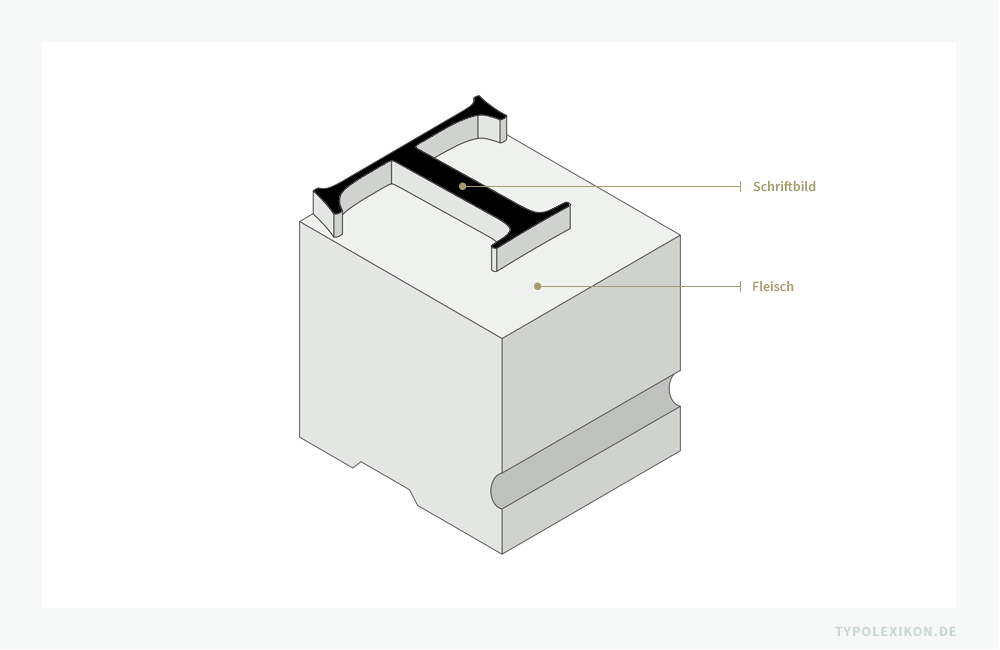
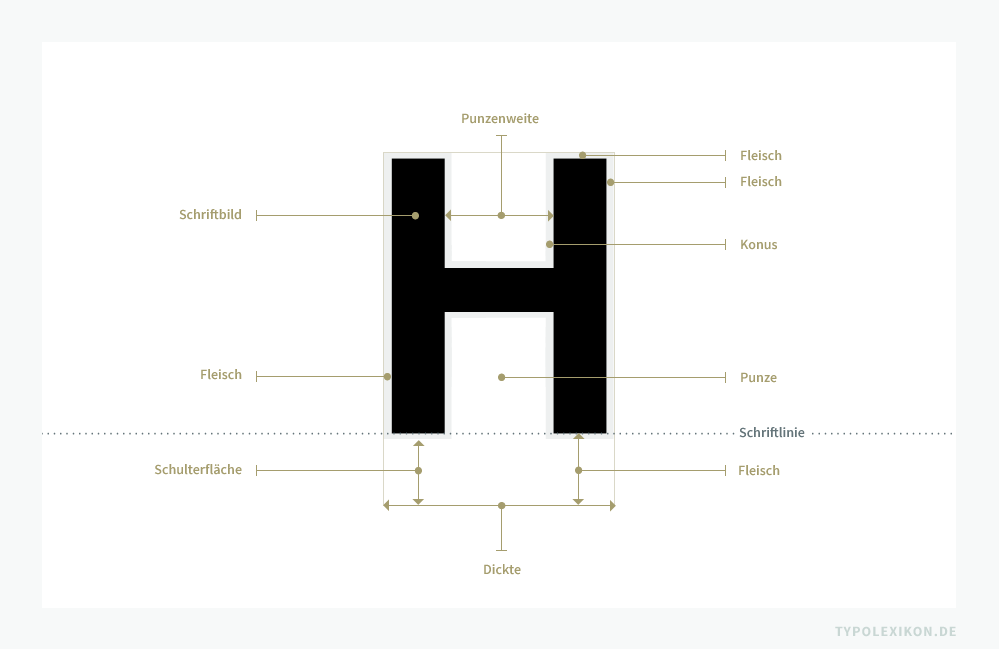Schema eines physischen Schriftkegels aus einer Blei-Zinn-Antimon-Kupfer-Legierung im normalen Breitenlauf.
Am Kopf eines Schriftkegels befindet sich das spiegelverkehrt erhabene (druckende) »Schriftbild« sowie das nicht erhabene (nichtdruckende) Fleisch inklusive Konus, Schulterfläche, Vor- und Nachbreite.
Bei physischen Drucktypen wird der gesamte nichterhabene Außenraum des Kopfes eines Schriftkegels als Fleisch bezeichnet, also alle nichterhabenen Flächen seitlich, ober- und unterhalb des erhabenen Schriftbildes eines Schriftkegels, unabhängig von Schulterhöhe, Konus, Vor- und Nachbreite. Bezugspunkte sind die äußersten Ränder des Schriftbildes und die beiden Seitenflächen, die Stirnseite und der Rücken des Kegelkopfes.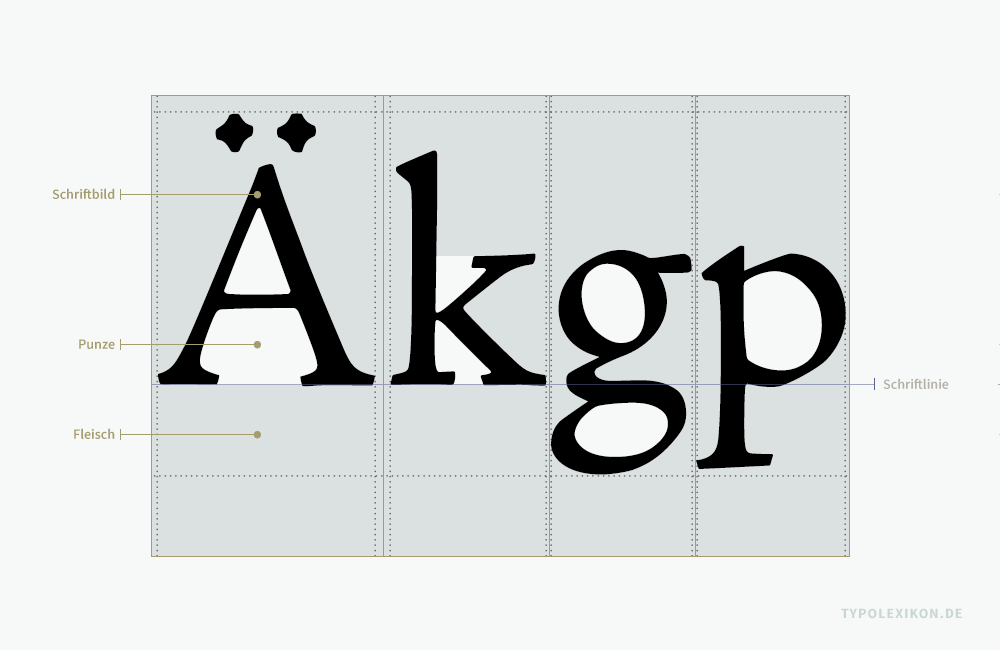
Das Fleisch bei digitalen Fonts
Bei digitalen Fonts wird der nichtdruckende Außenraum eines Schriftzeichens als Fleisch bezeichnet, also alle nichtdruckenden Flächen seitlich, ober- und unterhalb des Schriftbildes innerhalb einer koordinierten Fläche um das Zeichen. Bezugspunkte sind die äußersten Ränder des Schriftbildes und ein virtueller Bezugsrahmen, der alle Teile eines Schriftzeichens, inklusive seiner Formmerkmale, z.B. Striche, Bögen, Tropfen oder Serifen einschließt.
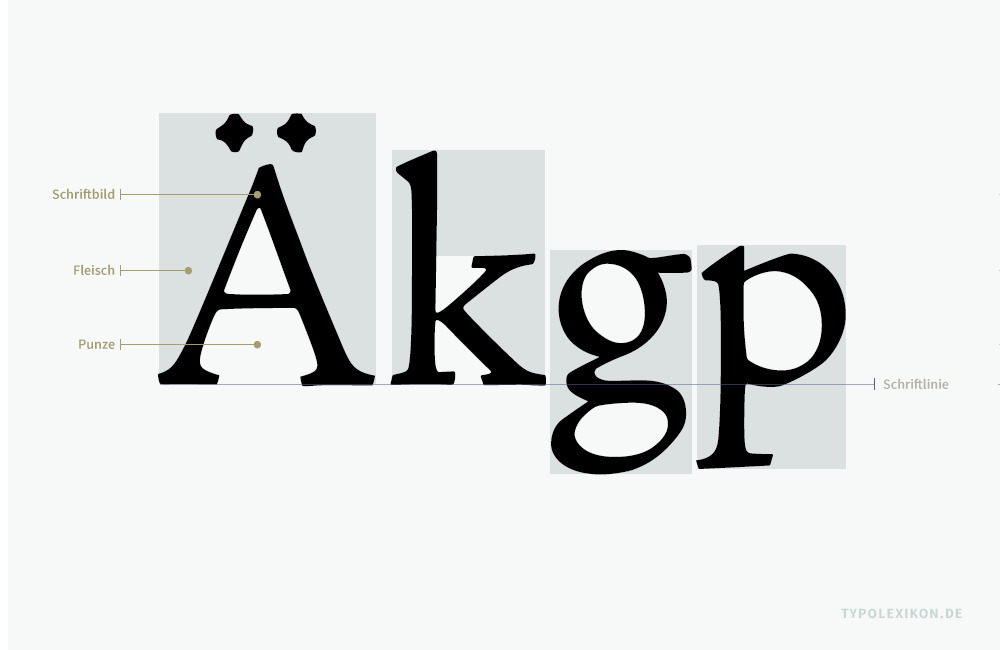
Bei digitalen Fonts wird der nichtdruckende Außenraum eines Schriftzeichens als Fleisch bezeichnet, also alle nichtdruckenden Flächen seitlich, ober- und unterhalb des Schriftbildes innerhalb einer koordinierten Fläche um das Zeichen. Bezugsgrößen sind die äußersten Ränder des Schriftbildes und ein virtueller Bezugsrahmen, der alle Teile eines Schriftzeichens, inklusive seiner Formmerkmale, z.B. Striche, Bögen, Tropfen oder Serifen einschließt.
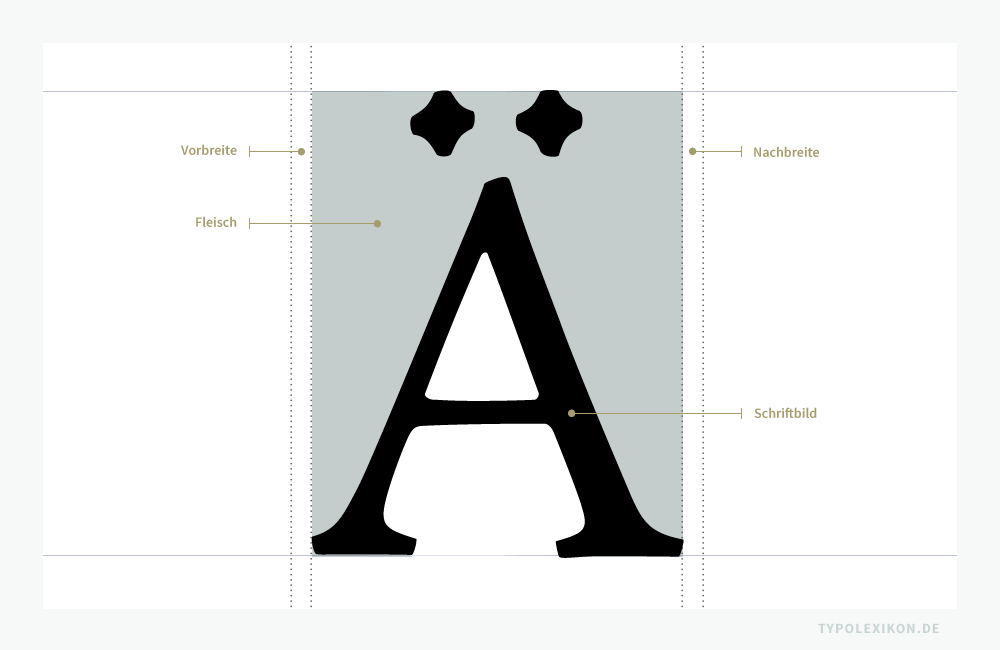Bei digitalen Fonts wird der nichtdruckende Außenraum eines Schriftzeichens als Fleisch bezeichnet, also alle nichtdruckenden Flächen seitlich, ober- und unterhalb des Schriftbildes innerhalb einer koordinierten Fläche um das Zeichen. Bezugsgrößen sind die äußersten Ränder des Schriftbildes und ein virtueller Bezugsrahmen, der alle Teile eines Schriftzeichens, inklusive seiner Formmerkmale, z.B. Striche, Bögen, Tropfen oder Serifen einschließt.
Die Vor- und Nachbreite eines Schriftzeichens grenzt bei digitalen Fonts direkt an das Fleisch bzw. an das Schriftbild, wird aber – im Gegensatz zu physischen Drucktypen – selbst nicht als Fleisch bezeichnet.
Die Vor- und Nachbreite eines Schriftzeichens grenzt bei digitalen Fonts direkt an das Fleisch bzw. Schriftbild, wird aber – im Gegensatz zu physischen Drucktypen – selbst nicht als Fleisch bezeichnet. Das Fleisch ober- und unterhalb eines Begrenzungsrahmens entfällt, da im DTP Desktop Publishing der Zeilenabstand über die Anwendersoftware, beispielsweise InDesign® von Adobe® oder QuarkXpress® von Quark®, flexibel geregelt wird.